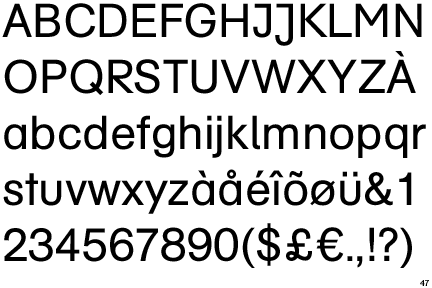
Eigenartige Helvetica-Abwandlung (a, u, M, R)
die AG ist nur als rounded drin, es ist aber eine DMschulbuch drin,
ich denke mal das DM bezieht sich auf 'Design Museum' und ist somit
wahrscheinlich ein corporate font.
Von der AG gibt es auch eine Schulbuch-Version:
Könnte die Pate gestanden haben? Und das große I und J wurden modernisiert? Das passende Suchwort lautet Schoolbook und nicht Schulbuch oder Fibel.